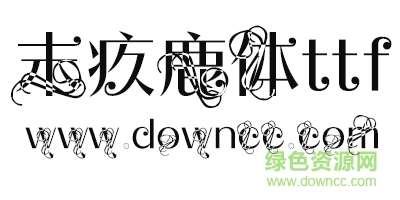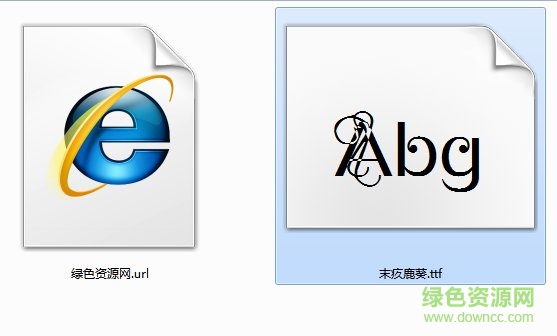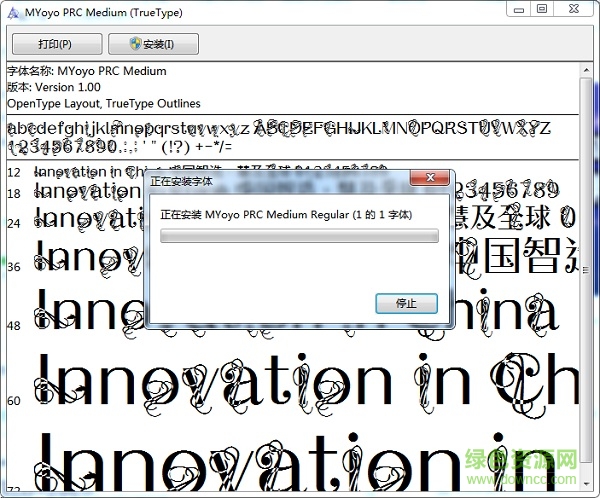
末疚鹿葵字體ttf英文版為大家提供了非常有創(chuàng)意的一款電腦字體。這款字體外形很個(gè)性化,主要用于設(shè)計(jì)一些創(chuàng)意性的廣告等。歡迎用戶下載安裝。
末疚鹿葵字體是一個(gè)免費(fèi)的創(chuàng)意字體。該字體線條粗細(xì)適中,每一個(gè)字都帶有花紋圖案,字形飄逸大方,整體效果非常的出色,可廣泛應(yīng)用于平面設(shè)計(jì)、廣告設(shè)計(jì)、報(bào)紙雜志、正文標(biāo)題等領(lǐng)域。喜歡的網(wǎng)友快來(lái)綠色資源網(wǎng)下載使用吧。